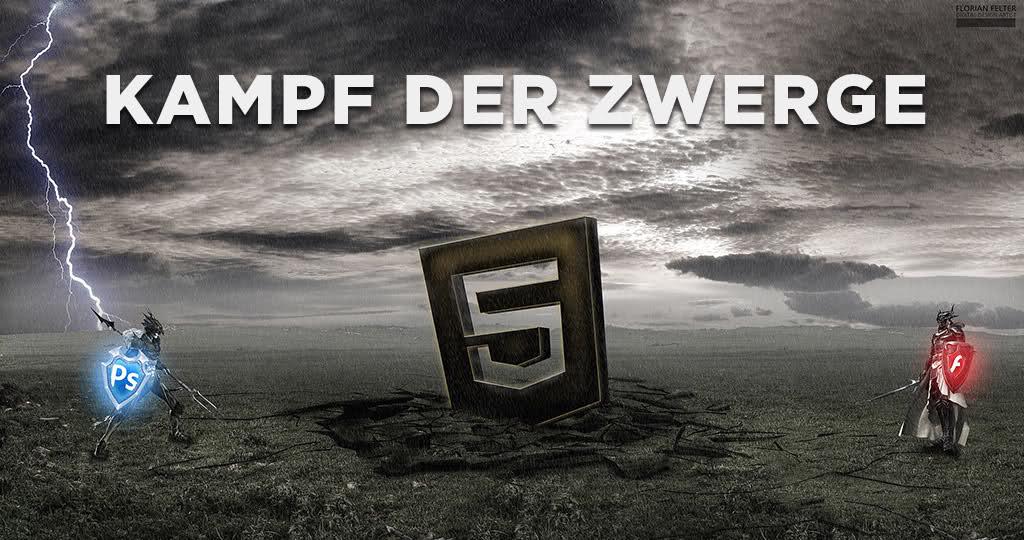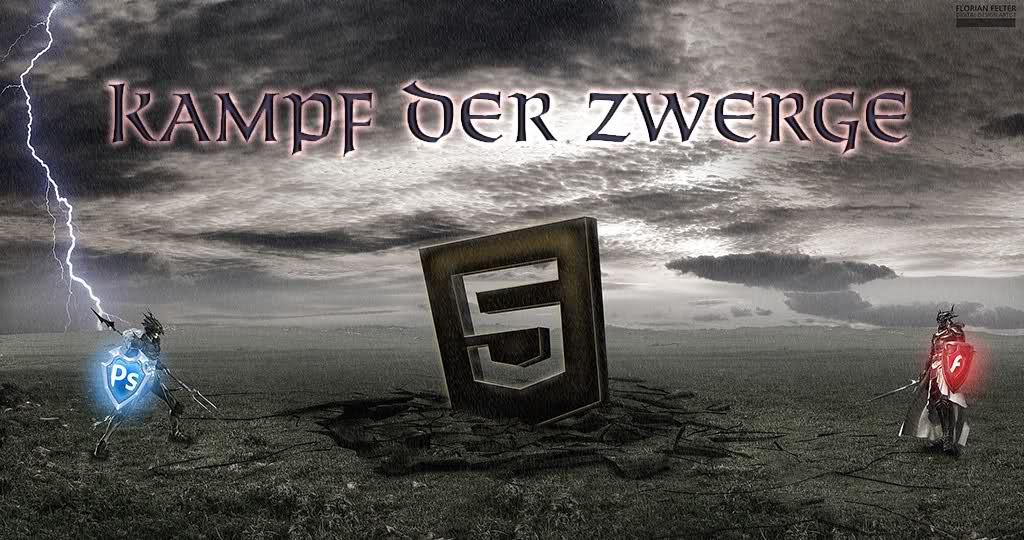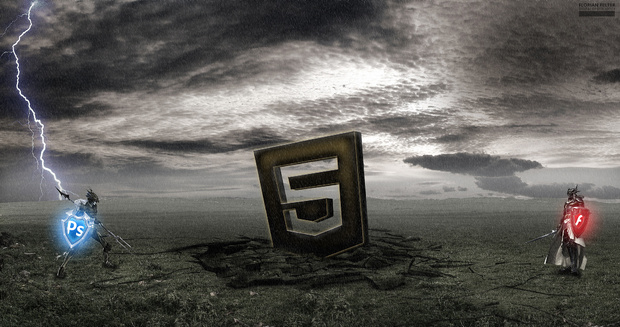
Schriftwahl für Titelbild
ich bin neu hier und möchte hier meine Fähigkeiten und mein Wissen zu Typografie weiterentwickeln. Ich arbeite momentan an einem Aufmacherbild für einen Magazinartikel. Es geht um Adobe HTML5 etc. Ich brauche dazu eine Schriftart die ein bisschen nach Schlacht und Kampf aussieht. (siehe Bild unten) Ich habe schon etliche ausprobiert doch komme einfach auf keinen Nenner. Für Tipps wäre ich sehr dankbar.
hey danke für die schnelle antwort. hmm.. kann auch was normales sein. muss halt einfach passen. dachte erst im tekken stil oder world of warcraft. aber war noch nicht das richtige dabei. aber schonmal vielen dank für den vorschlag.
Simeon sieht aber schon mal echt garnicht so schlecht aus.
… kann auch was normales sein …
Dann würde ich eine sehr kräftige, geometrische Schrift nehmen, vielleicht Gotham?
ich persönlich finde es muss ein mix aus fraktur und techno sein.
ggf. etwas bedrohlich, kommt aber auf die headline und die länge an.
da gibts nette fonts bei t26
oder donald beekman
oder ...
gibts in verschiedenen schnitten.
etwas zeitgemäßer?
einige der barnbrook fonts würden auch gut passen
(delux, mason, newspeak ...)
oder sowas?
auf klssische gebrochene schriften würde ich nicht zurückgreifen,
eine stencil passt eigentlich auch nich wirklich zum thema.
bertel`s 1. oder 2. ?? die ff pitu ist auch ein kandidat, finde ich.
Die Pitu muss halt groß genug verwendet werden, so dass man die „Klingenformen“ gut erkennt. Sie passt mehr zu Mittelalter etc., für die Laserschwert-Ecke sind Bertels Vorschläge vermutlich passender.